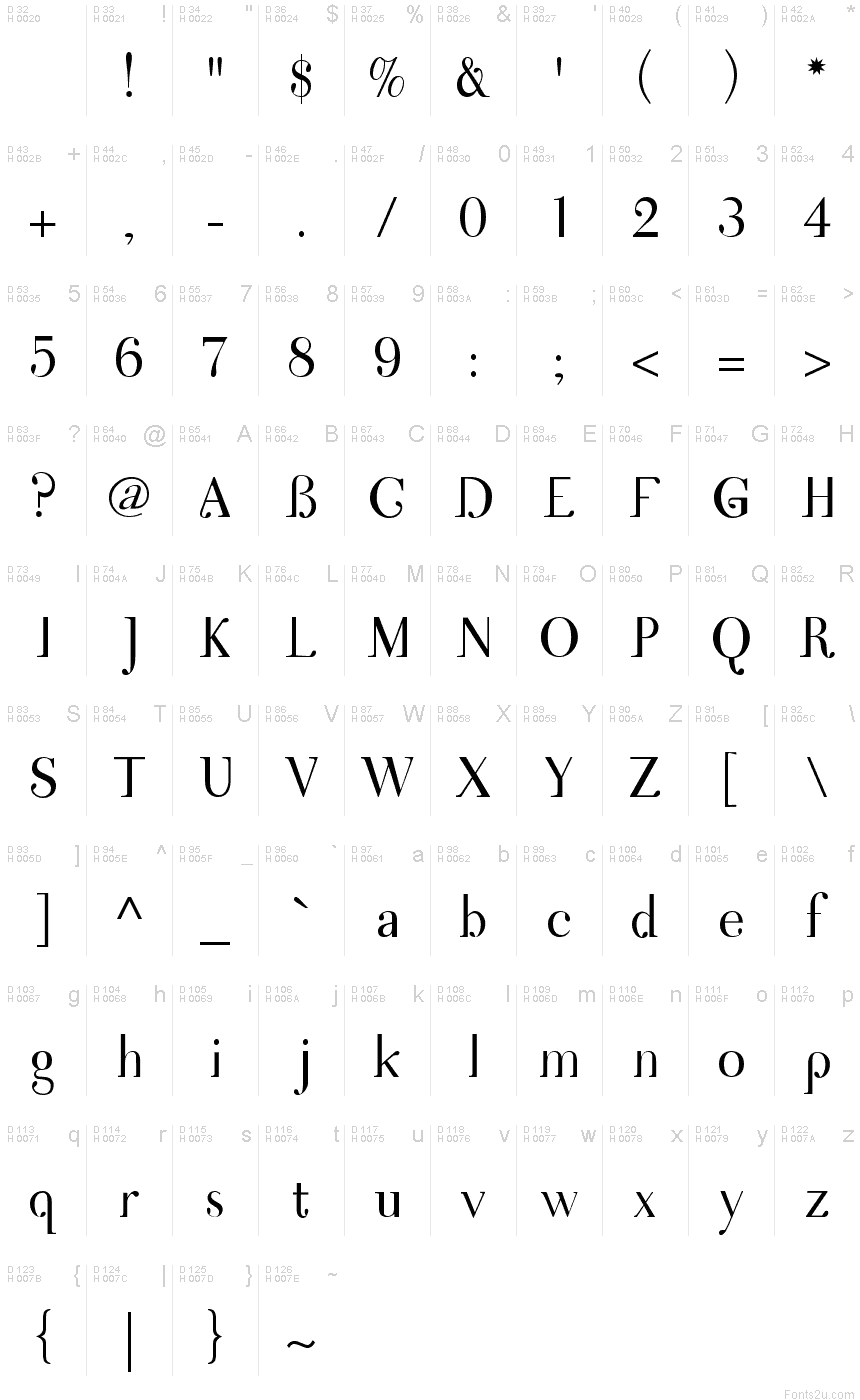
Nigma autorstwa Todda Michaela Bushmana to darmowy krój szeryfowy o wąskich literach, wyraźnych szeryfach i pełnym gracji, zapętlonym „g”. Całość cechuje spokojny, klasyczny rytm, który sprawia wrażenie formalnego, ale nie sztywnego.
Nigma świetnie sprawdza się na okładkach książek, w cytatach redakcyjnych, na zaproszeniach, w znakach logo oraz na opakowaniach, które wymagają wyrafinowanego szeryfowego charakteru. Kompaktowe kształty i eleganckie detale dodają wyrazistości krótkim tekstom, przy zachowaniu przejrzystości i harmonii.